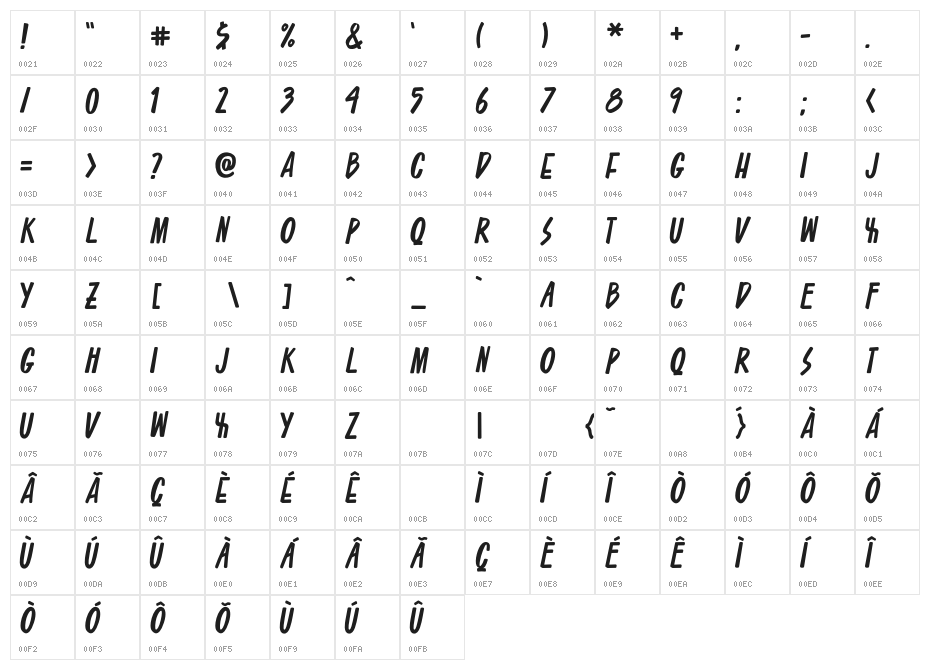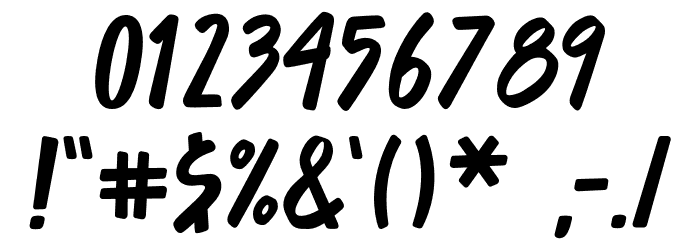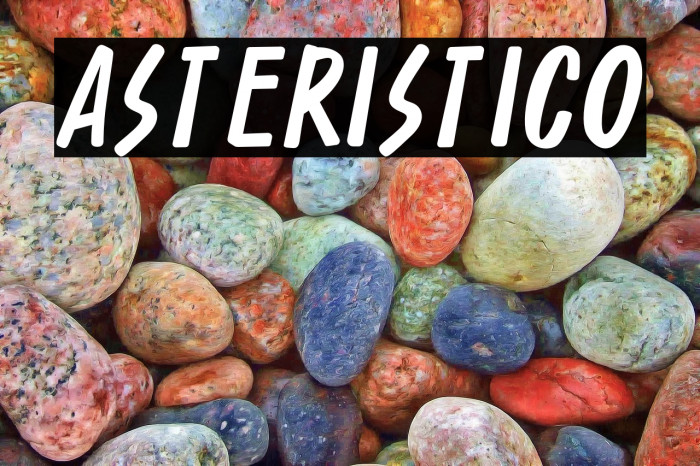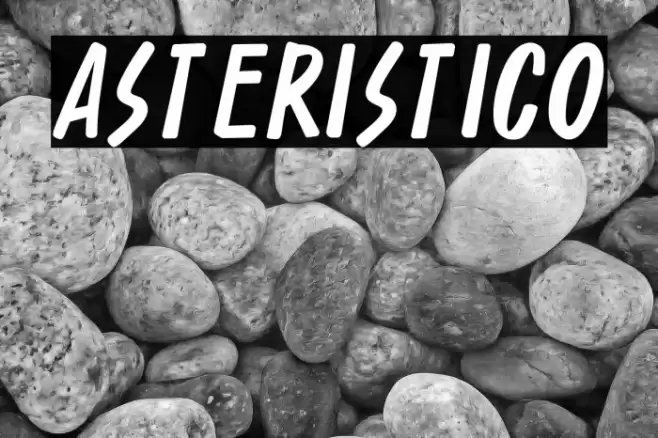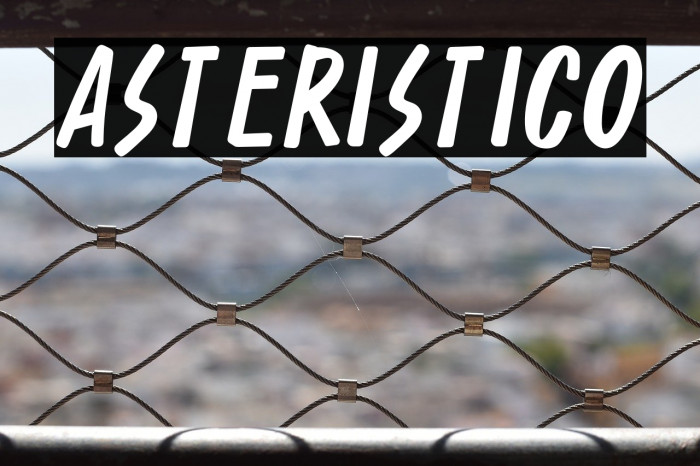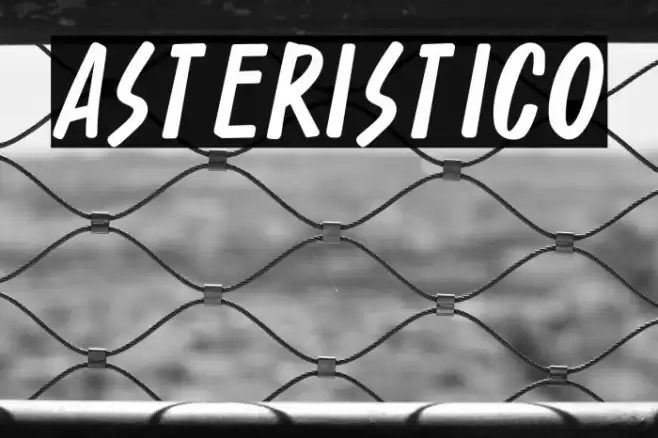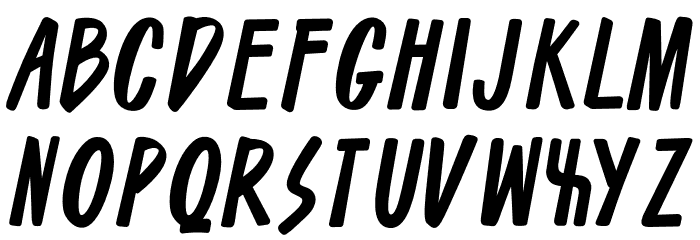
Asteristico Font
✎ Comic
| Proiecte propuse | Ideal for branding, posters, social media graphics, and any project that needs a lively and informal touch. |